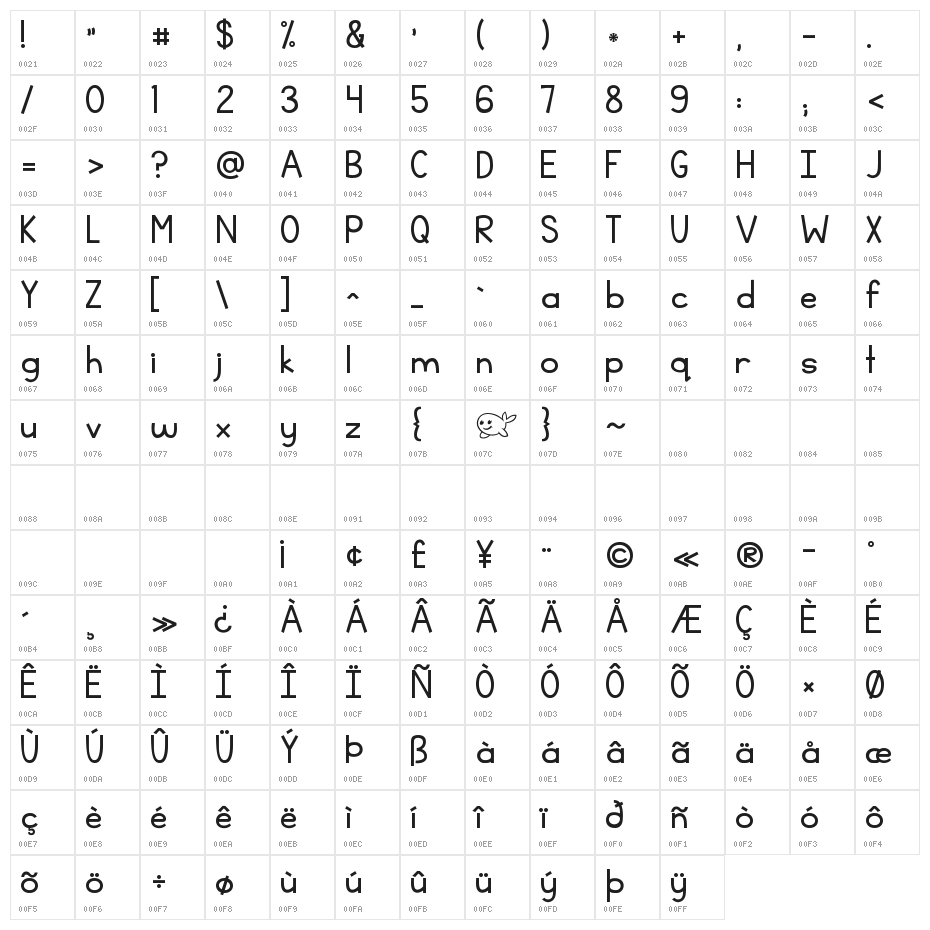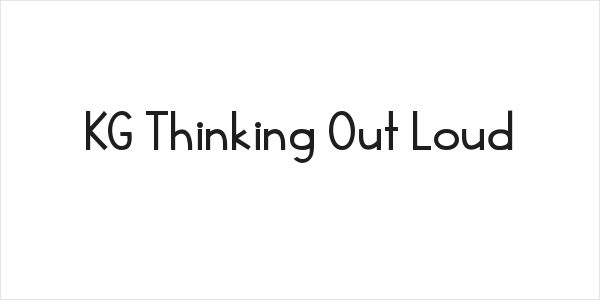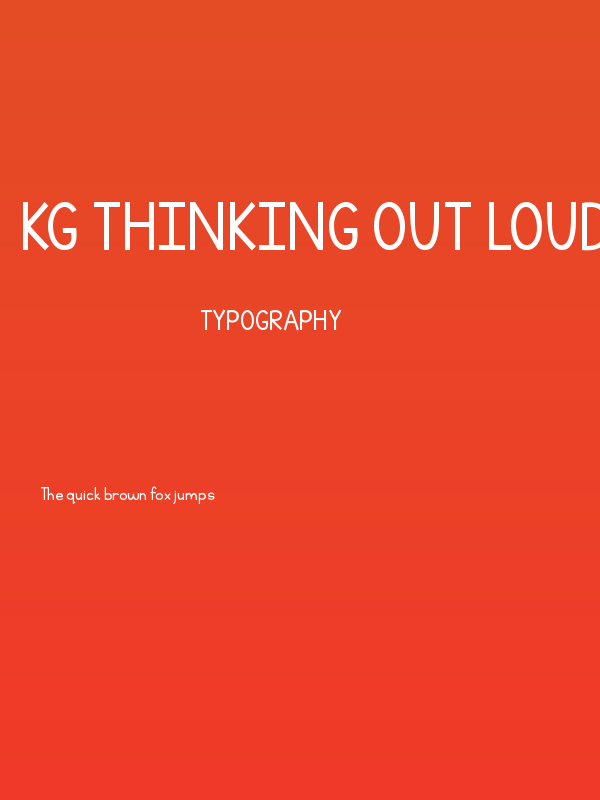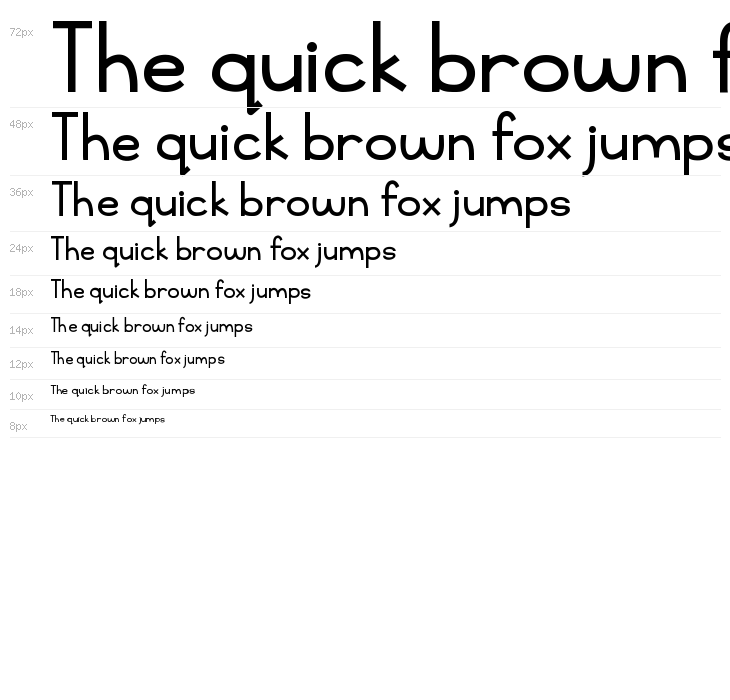
KG Thinking Out Loud Font
✎ Sans Serif
| Anwendungsfall | Headlines, Body text, Logos |
| Vorgeschlagene Projekte | Ideal for branding, advertising, web design, and editorial layouts due to its modern and clean appearance. |